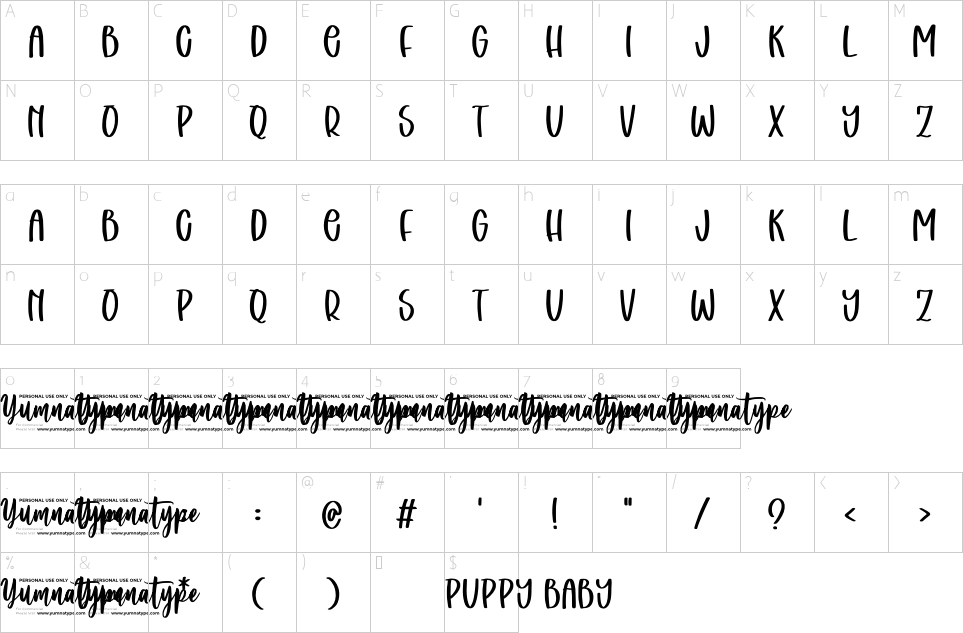
Descobrir uma nova fonte pode ser um verdadeiro presente para quem deseja dar um toque especial a seus projetos digitais. A fonte Puppy baby, criada pela Yumna Type, traz um toque divertido e carinhoso para seus materiais. Esta fonte infantil e delicada não só enriquecerá o seu layout de site ou design de aplicativos, mas também dará uma vibe amigável e alegre a qualquer projeto que você estiver trabalhando. Através de um design minimalista e delicado, esta fonte é ideal para gráficos de crianças ou para criar um design minimalista que seja agradável aos olhos. Com um download de mais de 11 mil vezes, a Puppy baby font já provou sua capacidade de se encaixar em diversos estilos. Instale-a em seus projetos e faça seu design brilhar ainda mais.